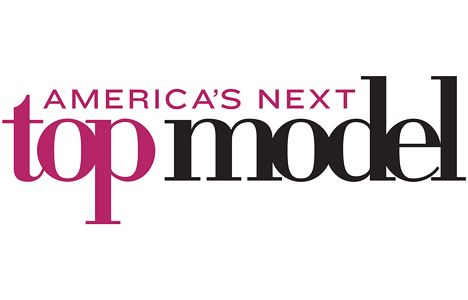
Welche Schrift ist Jung&Weiblich
ich hoffe eine der Profis kann mir helfen.
Und zwar suche ich für mein Vordiplom eine Schrift die jung und weiblich aussieht. Daraus möchte ich ein Logo für ein Produkt entwerfen, dass die Zielgruppe „JUNG&WEIBLICH“ anspricht. Doch leider mangelt es bei mir an der Schrifterfahrung. Ob da jemand spontan was einfällt.
Was für ein Produkt soll das denn sein? Suchst Du eher etwas scriptiges oder (auch) eine Textschrift?
Verarscht doch die Leute nicht so. Es gitb keine weibliche Schrift!
Es gibt evtl. Schriften die Frauen in einem bestimmten Kontext besser ansprechen. Schau Dir bitte mal einschlägige Modemagazine an. Bis auf Scriptschriften wirst du meist auf Groteskschriften ala Futura oder klassizistische Serifenschriften stoßen. Dolly und Co. sehen doch nach "dicke Wurst" aus. :hammer:
Wenn man an das durchschnittliche Übergewicht heutiger Teens denkt, liegt diese Assoziation ja vielleicht gar nicht so weit vom Thema ab.
wieso verar...? ich kann nur von meinem weiblichen bekanntenkreis reden, aber die würden, wenn man ihnen ein paar schriften hinlegt, eine dolly (kursiv) oder bello oder irgendeine andere scriptähnliche schrift einer futura oder bodoni vorziehen. bei einer antiqua würde meine freundin z.b die Arlt von pampatype eher nehmen, als die walbaum. etwas was weiche formen hat. es gibt wahrscheinlich keine frauenschriften, aber schriften, die einen großen teil an frauen eher ansprechen.
diese typischen klassizistischen sind doch gerade in diesem bereich schon so ausgelutscht worden und nur weil sie in einschlägigen modemagazinen verwendet werden, heißt das noch lange nicht, dass man sie deswegen immer nehmen muss.
außerdem hat er "jung" gesagt
Apropos Klassizistische und Konstruierte in leichten Schnitten – man müsste wirklich mal jungen Frauen ein schriftmäßig anders gestaltetes Mode-etc.-Magazin vorlegen. Siehe Sauna und meine Vorschläge. Und als Ultra Display Script noch die Mommie für die Großschau, das Ornament. Gibt es wahrscheinlich in England schon, kenne ich aber nicht … ich meine keinen coolen Trash a la Souvenir Light und kranke Fotos.
Au Mann, das erinnert mich an die Fragen nach "weiblichen" Illustrationen, denen man immer so begegnet. Das klingt dann immer so, als müsste man Frauen vor "richtigen" Bildern (oder in diesem Fall: Buchstaben) schützen: zarte Farben, leichte Linien, sanfte Irgendwas. Geäußert werden solche Wünsche von Frauen. Ach ja, und gestaltet werden kann so was dann natürlich auch nur von Frauen. :oops:
warum solls keine 'weiblichen' illustrationen geben?
es gibt doch auch kindliche zeichnungen, für kindern ...
simpler stil etc. für frauen sind die illust dann halt etwas
feiner gemalt. klar ist das alles sehr plakativ und oberflächlich
aber ich generell würde ich sagen das es schriften und illus
gibt, die frauen mehr ansprechen als männer. wobei es natürlich
auf die gesamterscheinung der gestaltung ankommt.
das finde ich schon sehr weiblich *hust* gemalt.
dazu dieser font:
Hehe, Norbert, ich glaube in deinem Illustrationsmetier hat man ziemlich viel Konkurrenz aus dem "Sektor Frau mit Ausdrucksambitionenen". So verzeihe ich dir :biglove:
Das schöne an diesem Thread ist doch, dass er (es) sich verselbstständigt – Estilo Script.
Robert, das sind genau die Klischeebeispiele, die ich meine. :cry:
Wer so einen Font für weiblich hält, findet auch Comic Sans lustig. :twisted:
Curlz, sage ich nur ...
Und hier haben wir Illus, die Frauen wirklich mögen (=kaufen) - aber sehen nicht doch eher männlich aus???
Das ist doch zu einfach … Baby-Manuals. Wo bleiben hier die jungen Frauen? Zumindest sehen die Titel anders aus, als PHP5-Manuals, die ja scheinbar für Männer gestrickt werden.
wie gesagt, klar sind das klischees ...
... aber zurecht. man kann auch mal klischees bedienen und muss
das rad nicht immer neu erfinden. die durchschnittsfrau und brigitte-
leserin kann sich damit identifizieren.